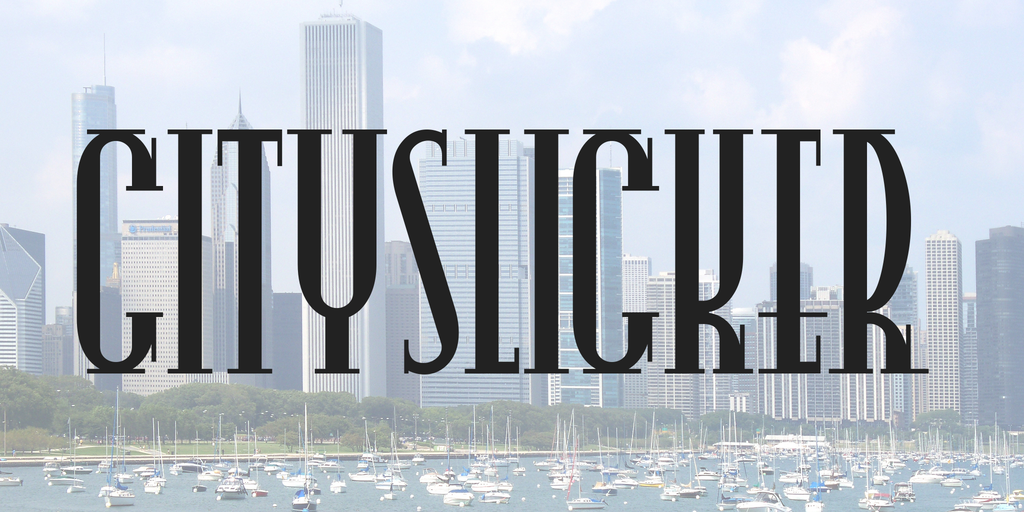
Aqui está uma descrição para a página de download da fonte CitySlicker Font: Com seu design elegante mas com um toque um pouco espinhoso e vibrante, a fonte CitySlicker é perfeita tanto para aplicativos como para criações digitais. Inspirada nos famosos Super Veloz Mr. Potato Head de Juan Trochut Blanchard, essa fonte apresenta uma espessura definida que adiciona um toque de vigor e estilo à sua mensagem visual. Sem dúvida, esta opção de letra Display é perfeita para aqueles projetos que exigem um pouco mais de atrevimento e presença. Seja para criar gráficos exuberantes ou design gráfico minimalista, a CitySlicker trará uma certa agilidade e energia ao seu trabalho. Inspirada em designs animados mas com um toque de sofisticação, esta fonte é uma excelente escolha para quem procura uma opção de letra versátil que mantém um ar moderno e vibrante. Com Hamilton como o designer responsável por essa criação única, a CitySlicker oferece um estilo único e vibrante para qualquer projeto em que você esteja trabalhando. Aproveite esta fonte para criar sua própria maneira de se expressar através do design visual.